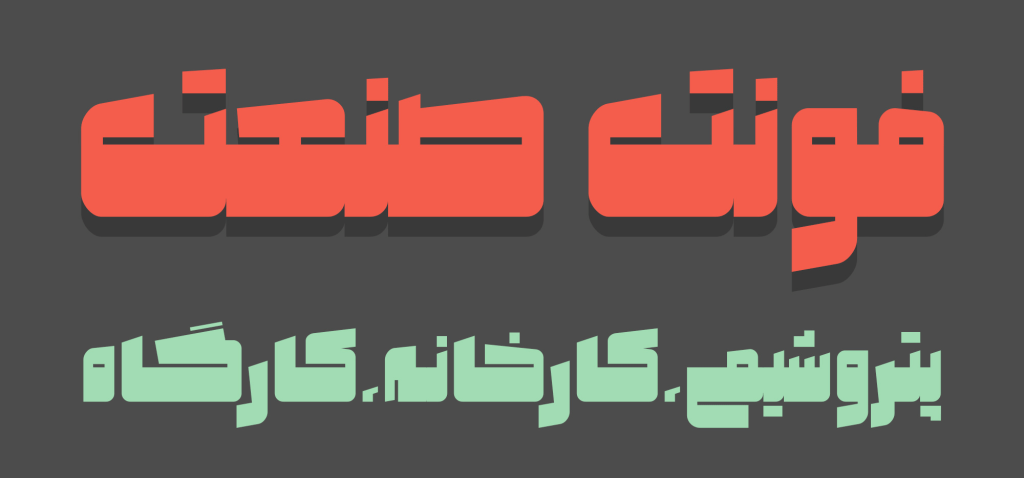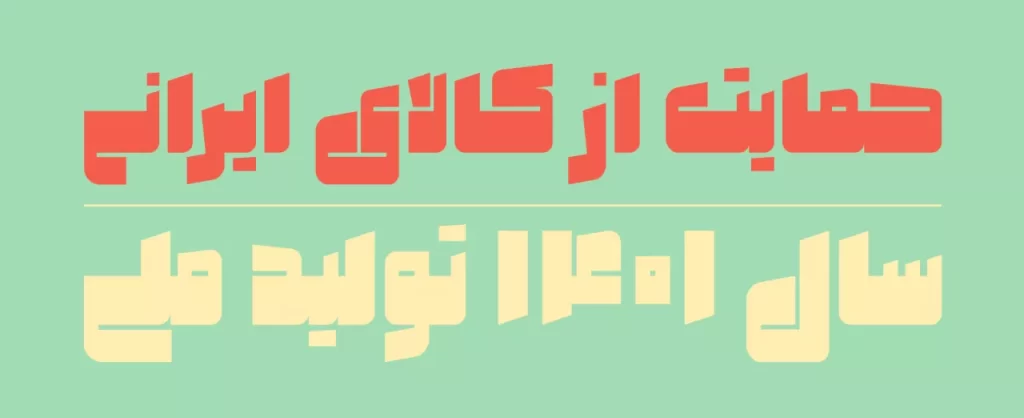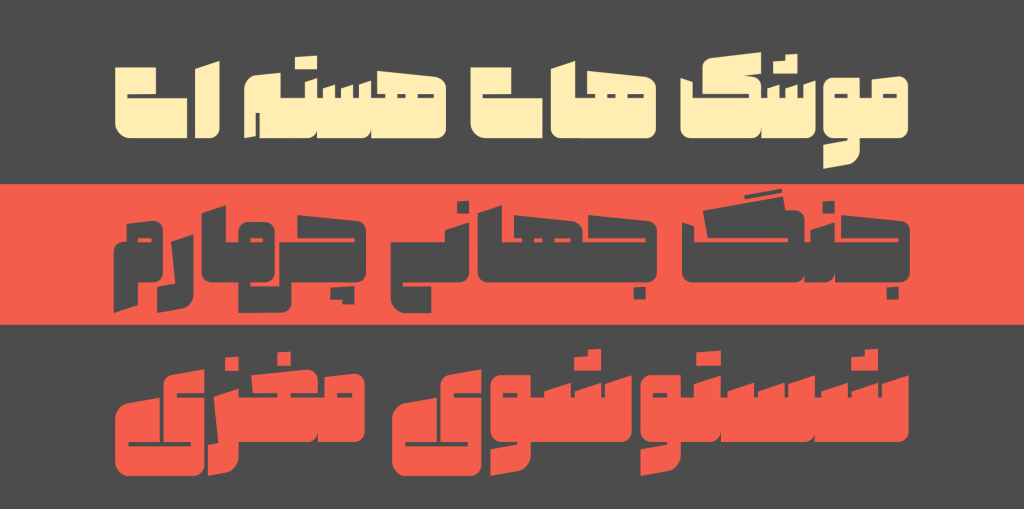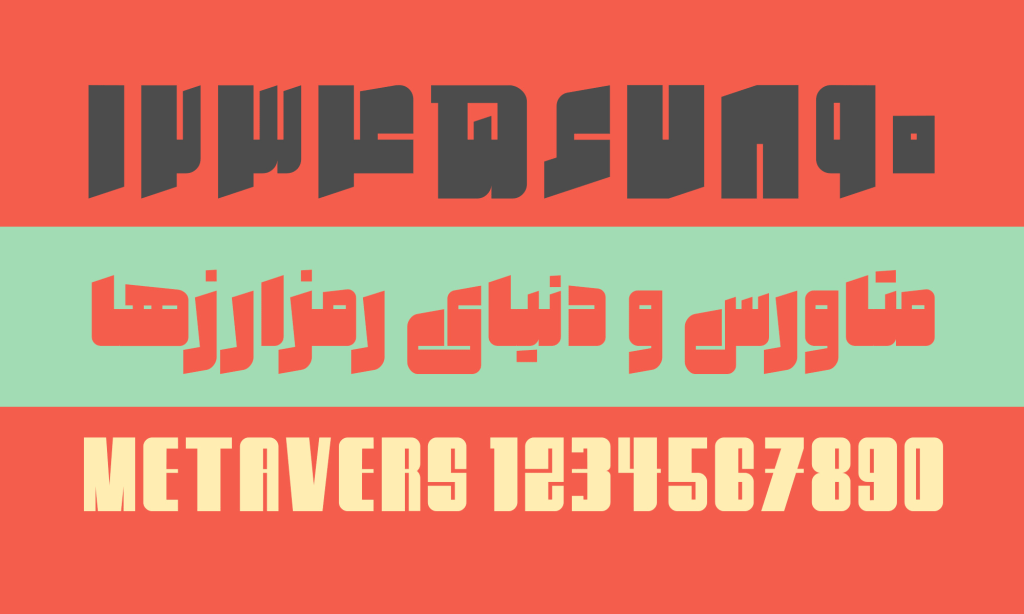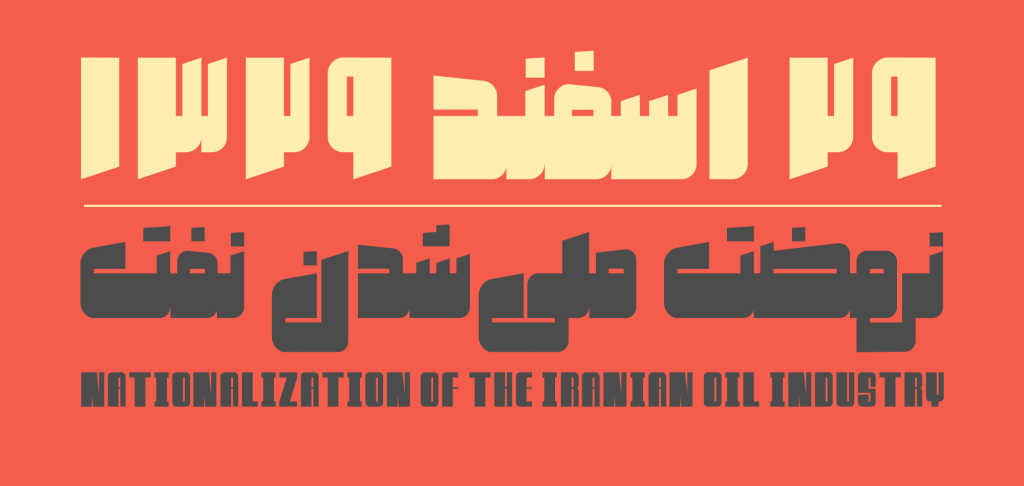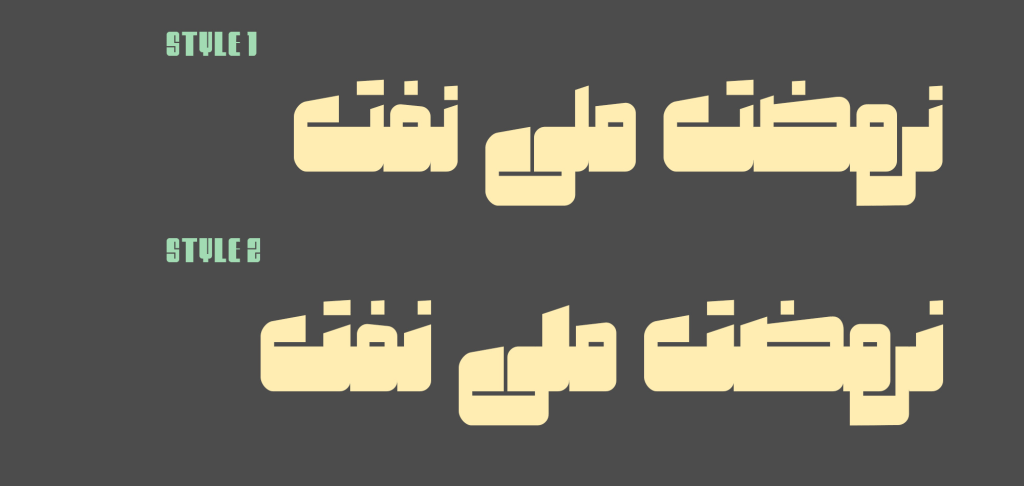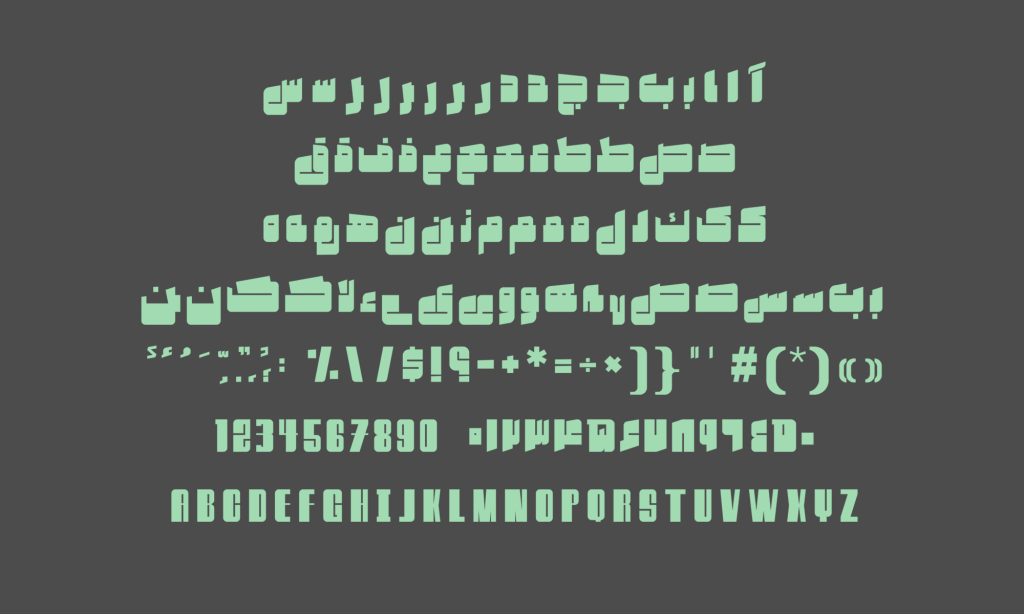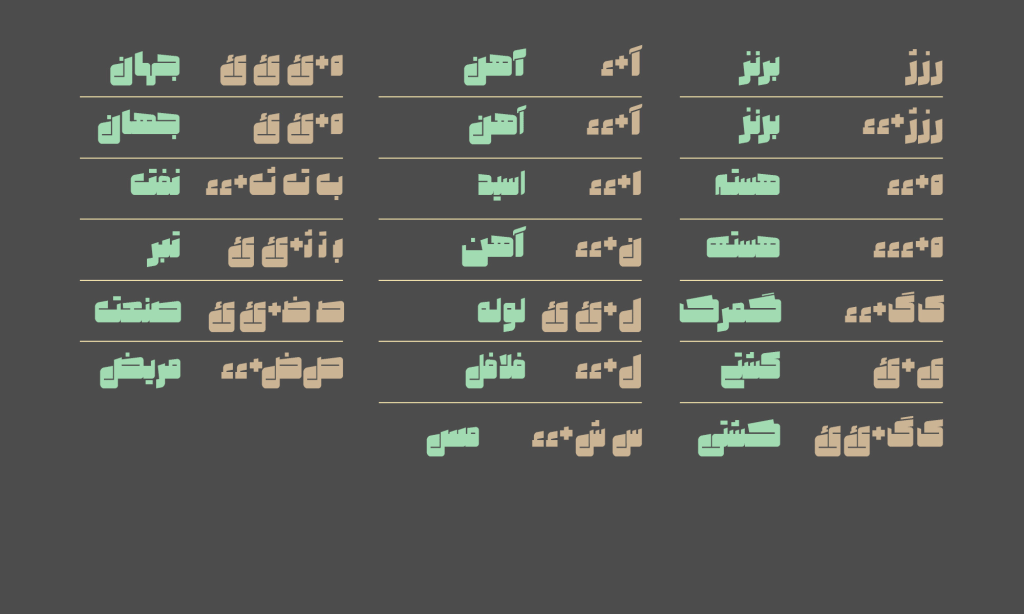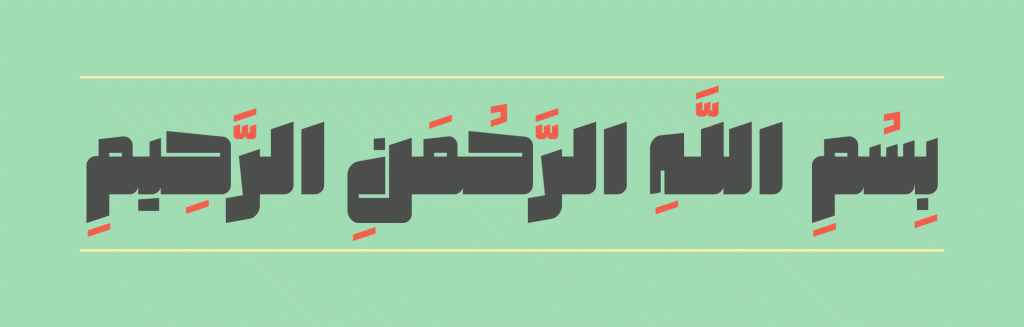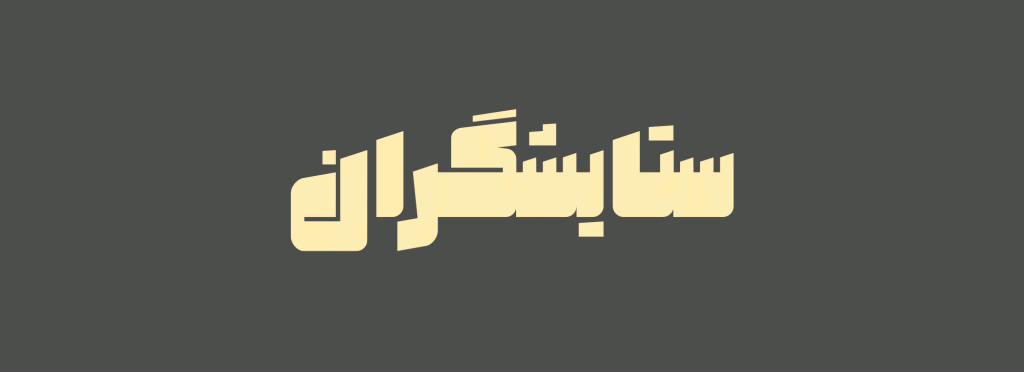
فونت صنعت
حروفی سنگین در فونت صنعت مورد استفاده در ساخت تابلو سردرها و لوگوتایپهای ماشینی مرسوم است. از همین روست که این تایپ فیس با وجود مدرن بودن دارای حس و حال نوستالژی و چکش کاری شده است.
طراح این تایپفیس (مجید شعرای نجاتی) میگوید: ایده اولیه این تایپ فیس از طراحی چندین لوگوی ماشینی شکل گرفت . نیاز به فونتی با وزن سنگین و ضخامت زیاد برای ایجاد کلماتی مناسب با فضای مورد نظر خود از اولین گام های شکل گیری این پروژه بود.
این قلم فقط یک وزن دارد اما دارای تعدادی حروف جایگزین است که میتوانید به دلخواه خود آن را تغییر دهید.